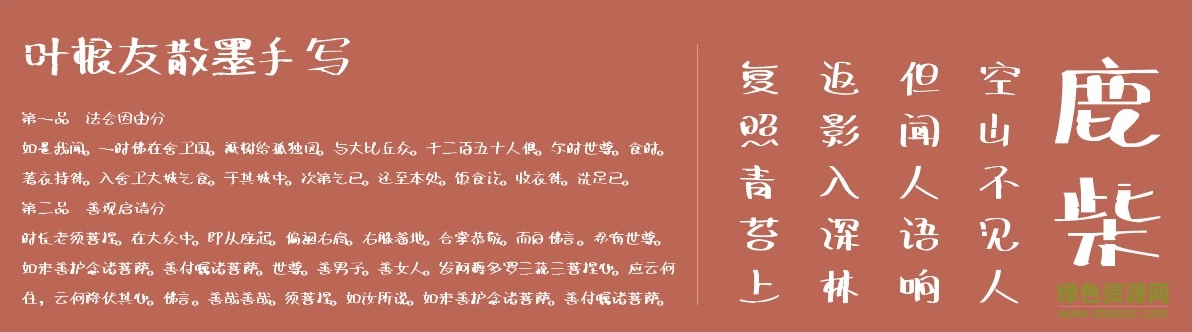
葉根友散墨手寫
葉根友散墨手寫字體是一款非常有特色的葉根友電腦字體,字體看上就非常的特別,并且給你很強(qiáng)烈的藝術(shù)設(shè)計(jì)感,有需要的朋友千萬不要錯(cuò)過,趕緊來綠色資源網(wǎng)下載吧!
字體簡(jiǎn)介
根友散墨手寫是一款手寫風(fēng)格的字體,字型干練而內(nèi)斂,在手寫體中尋求一種自我的突破。
葉根友散墨手寫字體